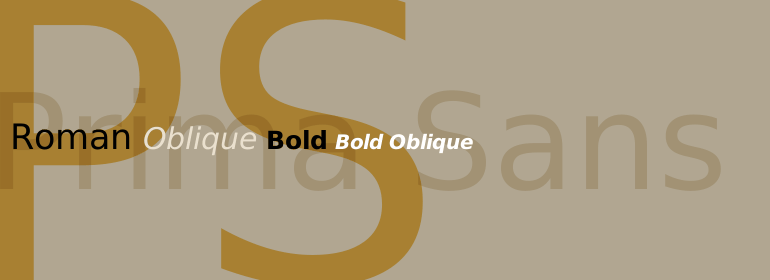
Prima Sans
Prima Sans,这款字体结构工整、笔画清晰,兼顾美观与易读性,适用于标题、正文、海报、包装、LOGO 等多种场景。字形优雅稳定,风格百搭耐看,适配日常排版与创意设计,让文字呈现更舒适、更具质感。Prima Sans一笔一画,皆是细节,以均衡的比例、流畅的线条打造舒适视觉体验,字形端正大气,风格简约现代。无论是商业设计、品牌宣传还是日常排版,都能轻松驾驭,让文字更有格调与力量。Prima Sans字体下载。
字体品牌: Bitstream(Monotype) 设计师:Lyles,Jim 字体分类:无衬线体 字体属性:外文 字符集:Unicode 发布时间: 2018